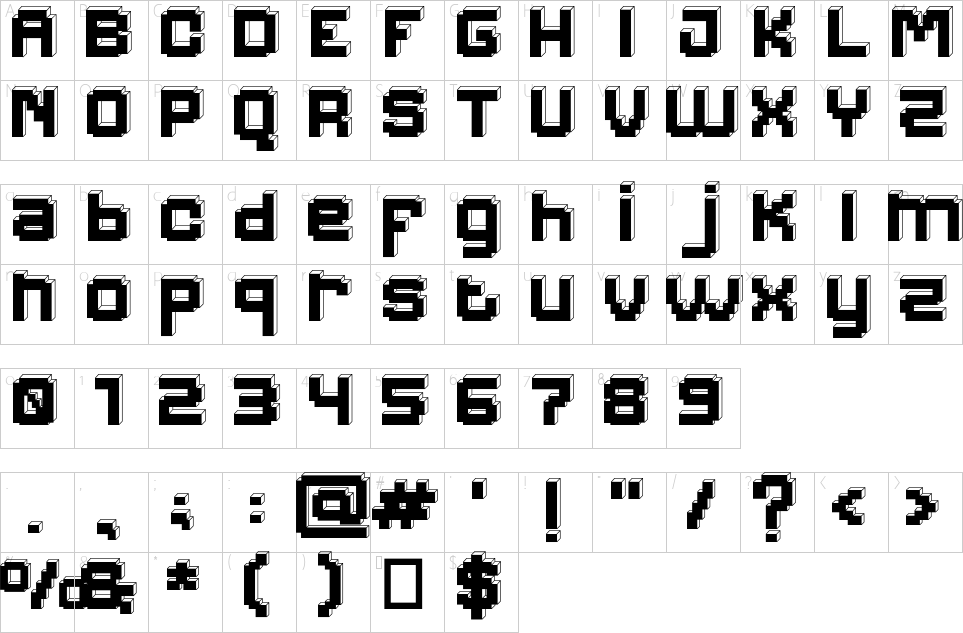
A Poxast Font é uma seleção gratuita para designers e amantes da arte digital, ideal para personalizar textos de forma única e moderna. Desenvolvida por Jada Akbal, esta fonte oferece um design elegante e minimalista, com linhas retas e letras geométricas que são perfeitas para criar designs minimalistas ou para um estilo mais sofisticado. Com sua facilidade de uso e versatilidade, Poxast é uma opção perfeita para designers digitais que procuram uma fonte que se destaca. Com a opção de baixar tanto para sistemas Windows quanto para Mac, você pode garantir um design consistente em todos os seus dispositivos. Sua versão gratuita, ainda assim, oferece um alto nível de qualidade e estilo, ideal para quem busca uma fonte de alta qualidade sem precisar gastar. Com 1,053 downloads desde seu lançamento, você pode estar certo de que a Poxast Font é uma fonte de alta qualidade que merece uma chance.